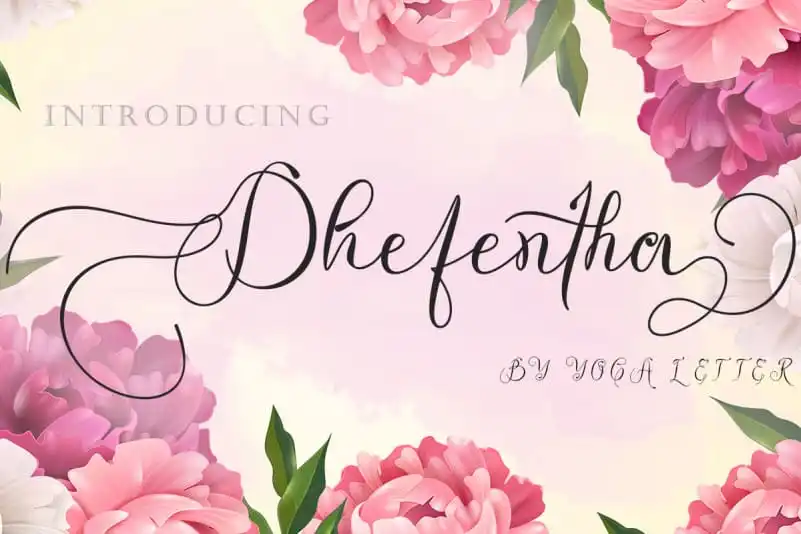
Dhefentha Calligraphy Font – Fonte Grátis
Dhefentha Calligraphy Font
Dhefentha Calligraphy Font é uma elegante escolha para qualquer tipo de trabalho que você possa precisar. Desenvolvida por Yoga Letter, esta fonte tem uma textura suave e delicada, resultando numa impressão única e encantadora. Ela se adapta perfeitamente a diversas necessidades, sendo perfeita para requisitos relacionados à cerimônia de casamento – desde convites, tiras de câmera de cerimônias, decorações até designs exclusivos do evento. Além disso, ela é uma opção sólida para promover seu negócio – seja hotel, residência, locais para lazer ou produtos e serviços – a qualquer ocasião especial como aniversários, natal ou festas invernais. Dhefentha Calligraphy Font também é perfeita para atualizações de promoção, logos, materiais promocionais, postagens nas mídias sociais e muito mais. Sem dúvidas, ela encaixa-se perfeitamente em seu trabalho gráfico com uma textura suave que não se sobrepõe às suas necessidades específicas.